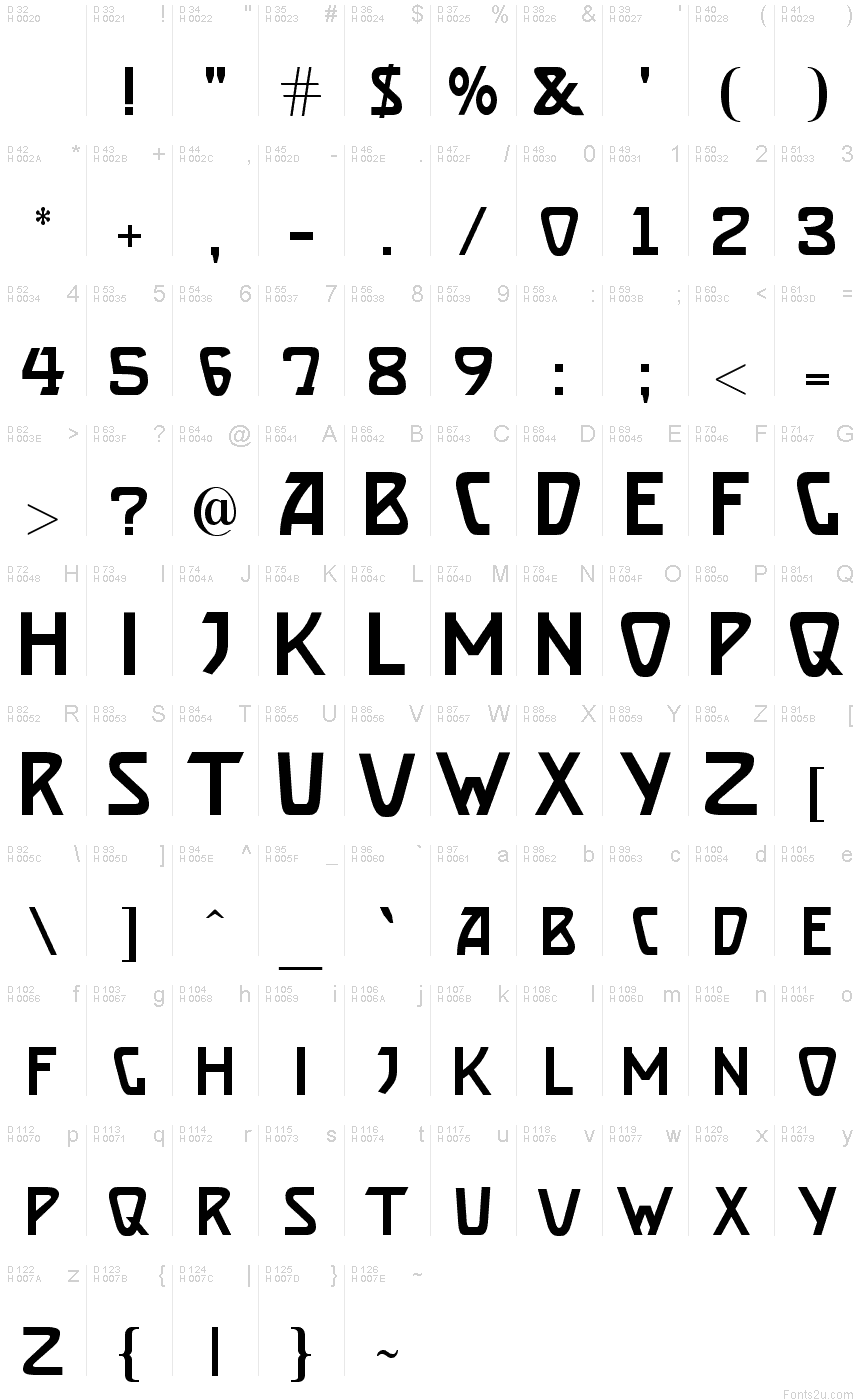
Brassett من PJL هو خط عرض (display) مجاني بلمسة ريترو وتصميم هندسي حاد، يوحي بجماليات لوحات الألعاب القديمة أو لافتات المعدن المصقول. تمنح القصوص القطرية الحادة والخطوط العريضة والمتزنة للكلمات إيقاعاً ميكانيكياً سريعاً، مما يجعل العناوين القصيرة تبدو قوية ومؤثرة دون أن تكون ضخمة.
يعتبر Brassett خياراً رائعاً لعناوين الملصقات، وأغلفة الألبومات، وتصاميم الألعاب، ومفاهيم الشعارات، ومنتجات الرياضة، والصور المصغرة لليوتيوب، ومنشورات الفعاليات التي تتطلب طابعاً قديماً (vintage) بحواف نظيفة. يظهر هذا الخط المجاني بأفضل شكل في الأحجام الكبيرة؛ استخدمه مع خط "sans" بسيط مثل Inter أو Helvetica للحفاظ على حيوية الطابع الكلاسيكي بشكل واضح.